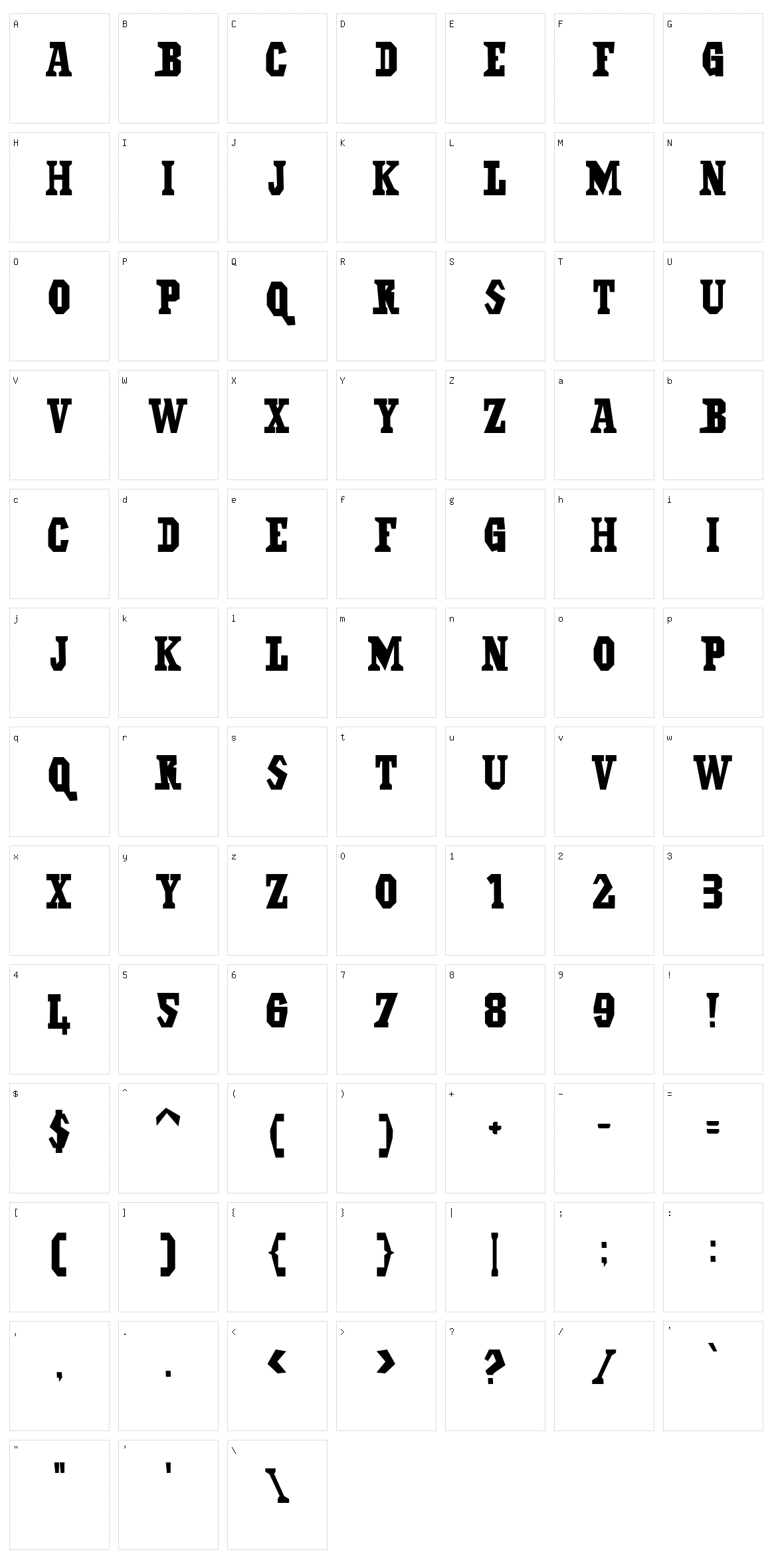
x IL GRINTA FONT x
x JOHN WYNE COLLECTION x
Font name: IL GRINTA (John Wyne Collection) - Latin Decorative font (versione 1.0)
Type designer: P. A. Vannucci
IL GRINTA font: direttamente dal film diretto da Henry Hathaway e interpretato da John Wyne, il font inedito per tutti
gli estimatori del film. Da notare il ritocco necessario in Photoshop per conferire, alla titolazione, l'originale bordatura.
TRUE GRIT font: directly from the Best movie by Henry Hathaway, with John Wyne,